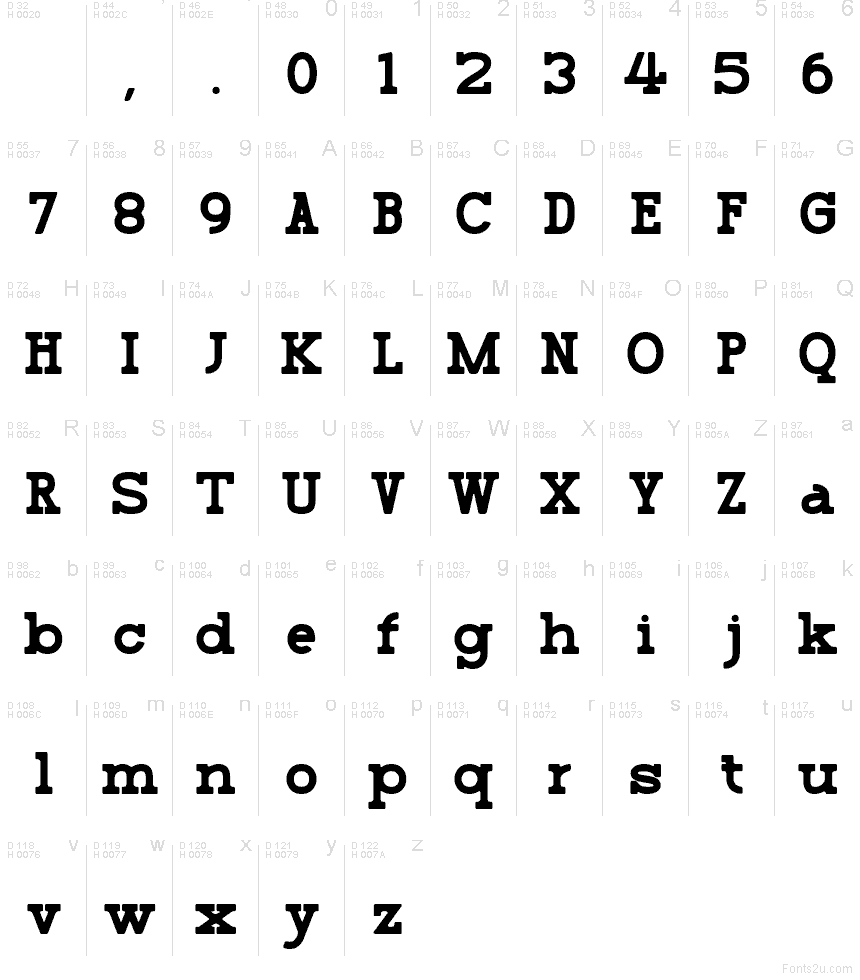
Rambone Regular
Rambone od Muksal Creative je bezplatné písmo so zaoblenými pätkami, kompaktnými krivkami a pevným, klasickým štýlom znakov. Tvary sú stabilné, bez ostrých hrán, a opakujúce sa výrazné pätky dodávajú tejto rodine uzemnený, jemne vintage charakter.
Rambone je bezplatný font, ktorý skvele vynikne v titulkoch na plagátoch, logách, obaloch, knižných obálkach či krátkych redakčných akcentoch, kde sa žiada silný patkový hlas. Vďaka svojim pevným tvarom a jemným rohom sa hodí aj na etikety, označenia a reklamné predmety, najmä keď dizajn potrebuje vzhľad písma s klasickým, remeselným nádychom.